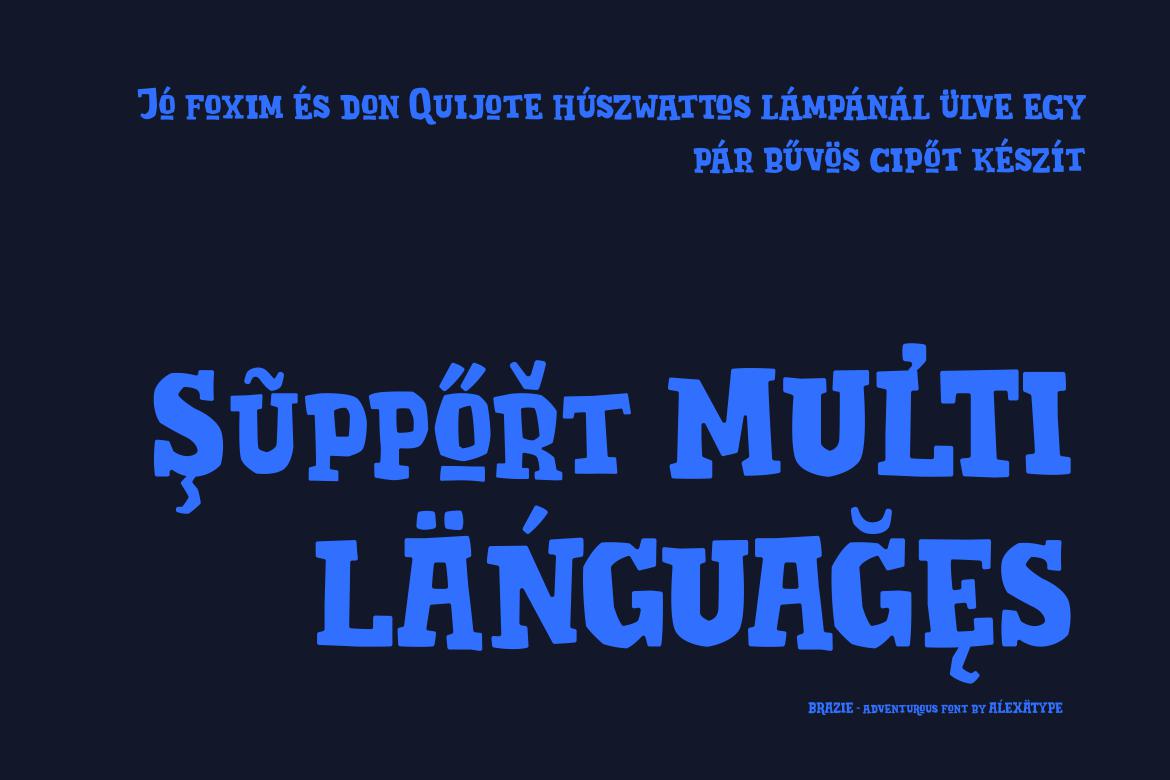
使用ErifshapeandBouncyBaseline,BraziebringonaldClassicWesternstyleFontwithafunvibes。适用于任何户外活动海报、旅行博客、旅游海报等。使用ErifshapeandBouncyBaseline,BraziebringonaldClassicWesternstyleFontwithafunvibes。适用于任何户外活动海报、旅行博客、旅游海报等。